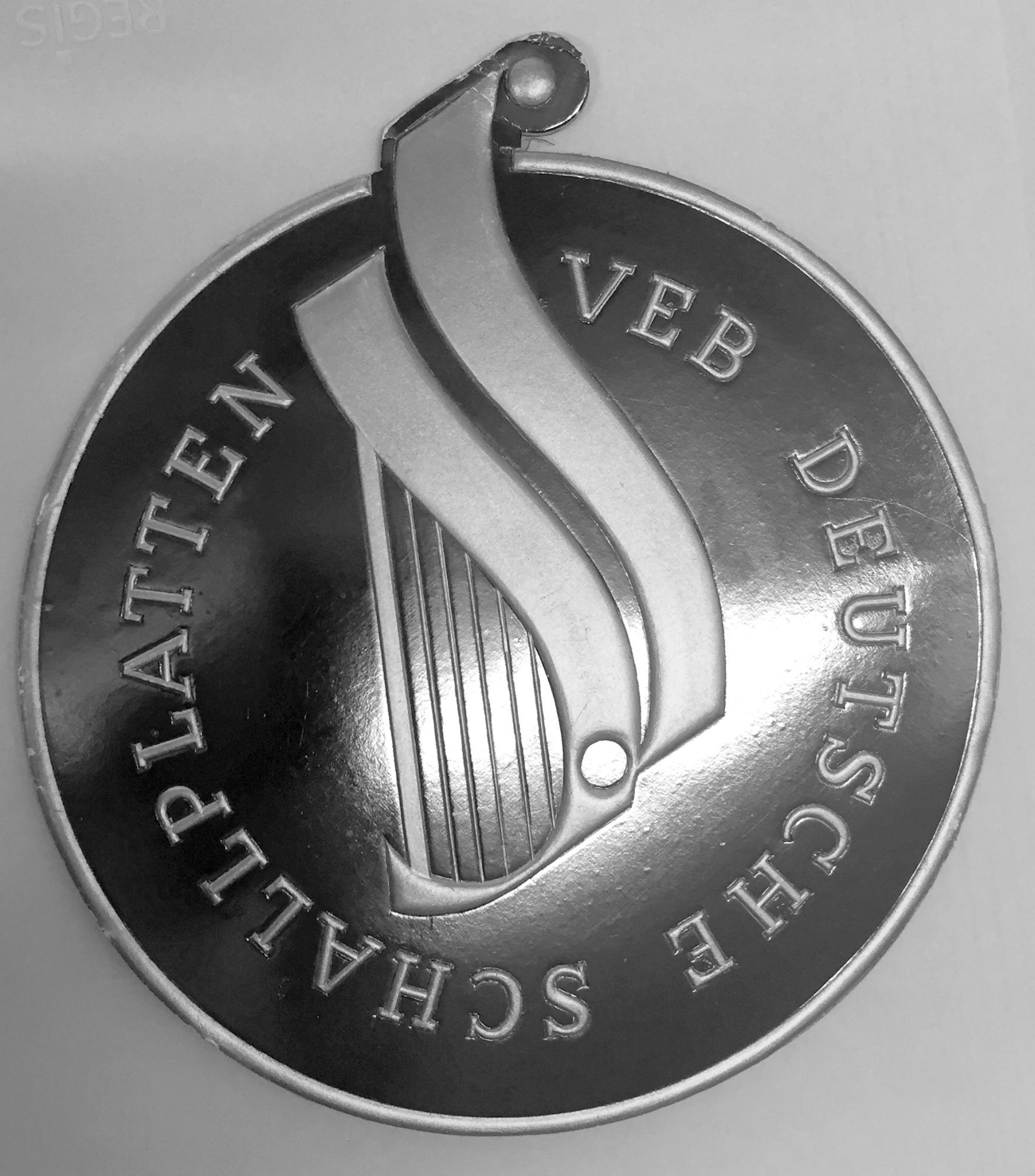
Schrift von VEB DEUTSCHE SCHALLPLATTEN
Mittlerweile kenne ich mich mit den Schrift der DDR schon ganz gut aus. Trotzdem hab ich heute mal wieder eine Frage. Vielleicht kann einer von euch mir helfen herauszufinden, welche Schrift für die Wort-Bild-Marke "VEB DEUTSCHE SCHALLPLATTEN" verwendet wurde. Ich selbst dacht an die Baltica, wollte aber noch eure Meinung dazu wissen. Gerade das "E" spricht vielleicht doch für eine andere Schriftart. Vielen Dank für alle Antworten.
Klar, das kann natürlich auch sein. Man kann die Buchstaben auch nachzeichnen. Durch die Produktionsart (hier die nicht all zu präzise Prägung) verändern sich die Buchstaben jedoch immer mehr oder weniger. Daher möchte ich nichts unversucht lassen, um dem Original so nah wie möglich zu kommen.